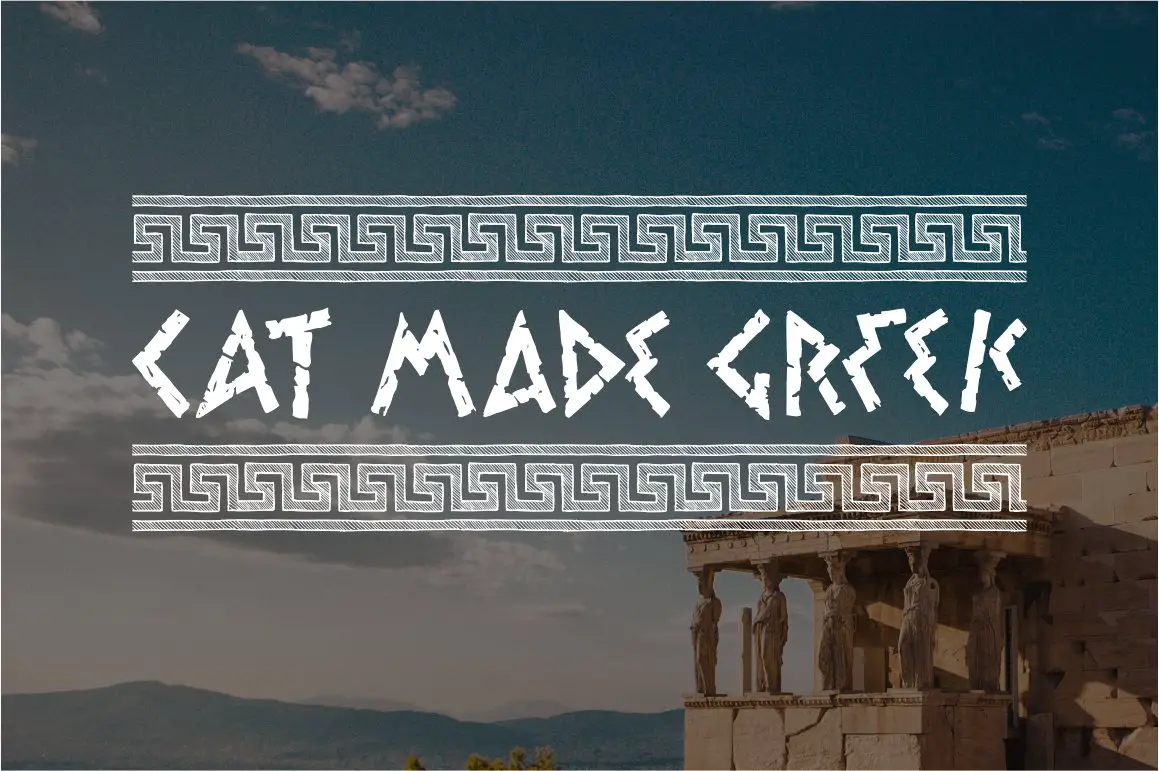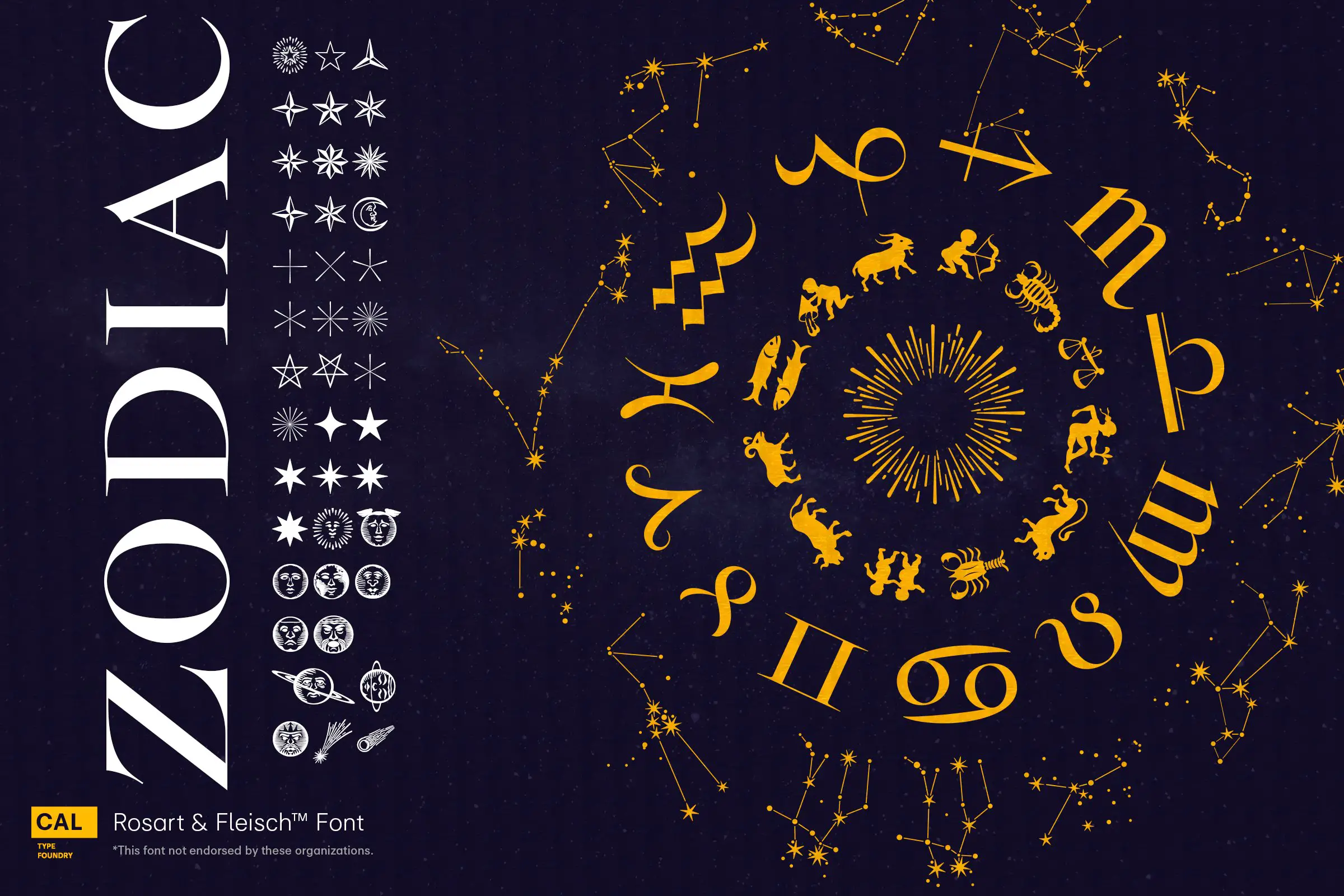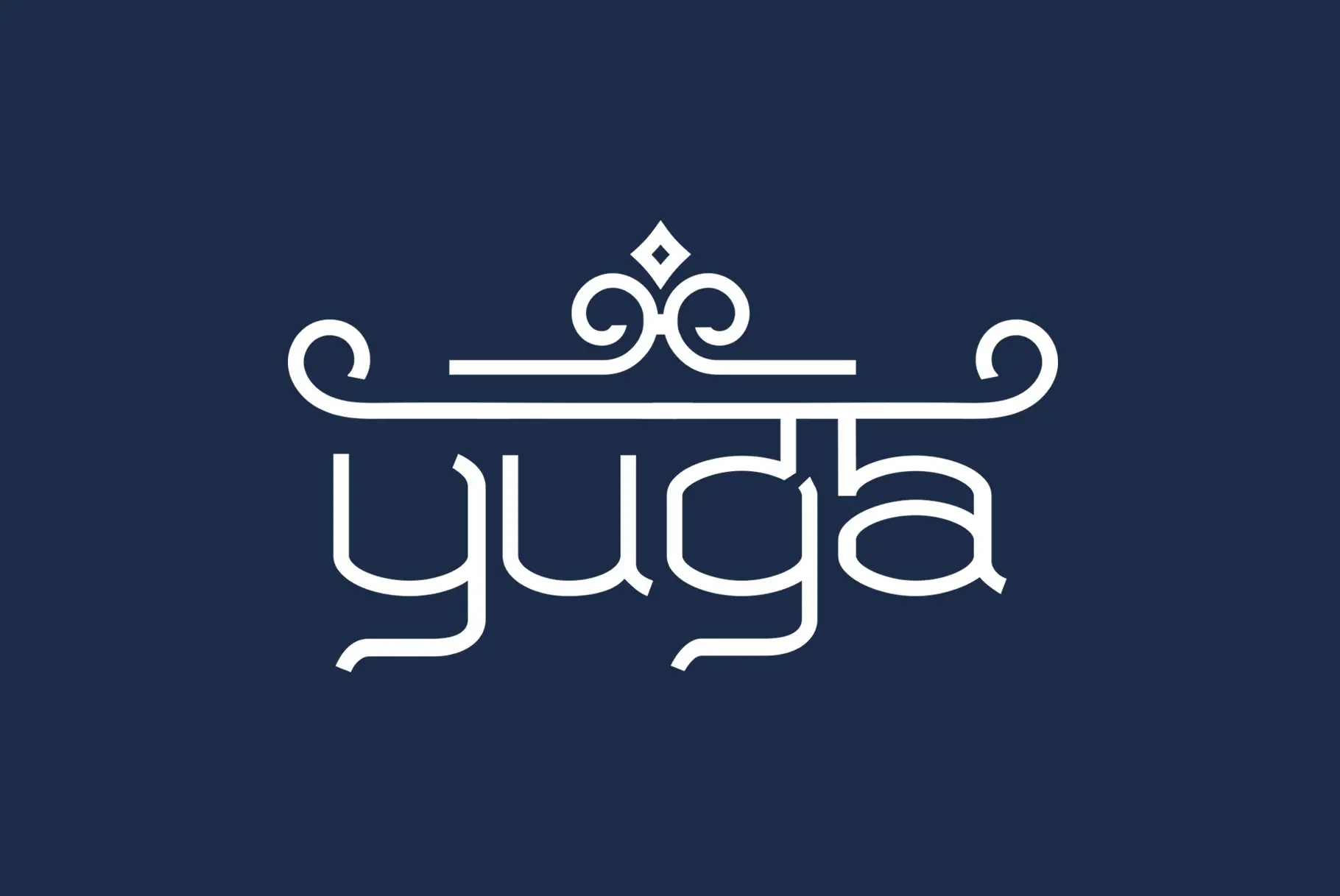
Die 16 besten Bangla-Schriftarten 2023
Veröffentlicht: 2023-05-16Sind Sie ein Grafikdesigner und suchen nach der perfekten Bangla-Schriftart, um das Design Ihres Projekts zu verbessern? Suchen Sie nicht weiter! Unser Artikel über die 16 besten Bangla-Schriftarten bietet Ihnen alles.
In diesem Artikel haben wir eine Liste der 16 besten Bangla-Schriftarten zusammengestellt, die Ihre Designs auf die nächste Stufe heben. Bei über 300 Millionen Bangla-Sprechern weltweit ist es wichtig, die richtige Schriftart zu haben, um Ihre Botschaft effektiv zu kommunizieren. Unsere Auswahl umfasst Schriftarten, die sowohl schön als auch gut lesbar sind und dafür sorgen, dass Ihre Designs hervorstechen.
In diesem Beitrag stellen wir Ihnen jede unserer handverlesenen Bangla-Schriftarten vor und geben Einzelheiten zu ihren einzigartigen Funktionen und Vorteilen. Ganz gleich, ob Sie für eine Website, einen Druck oder soziale Medien entwerfen, diese Schriftarten tragen dazu bei, dass Ihre Arbeit professionell und elegant aussieht.
Elodie
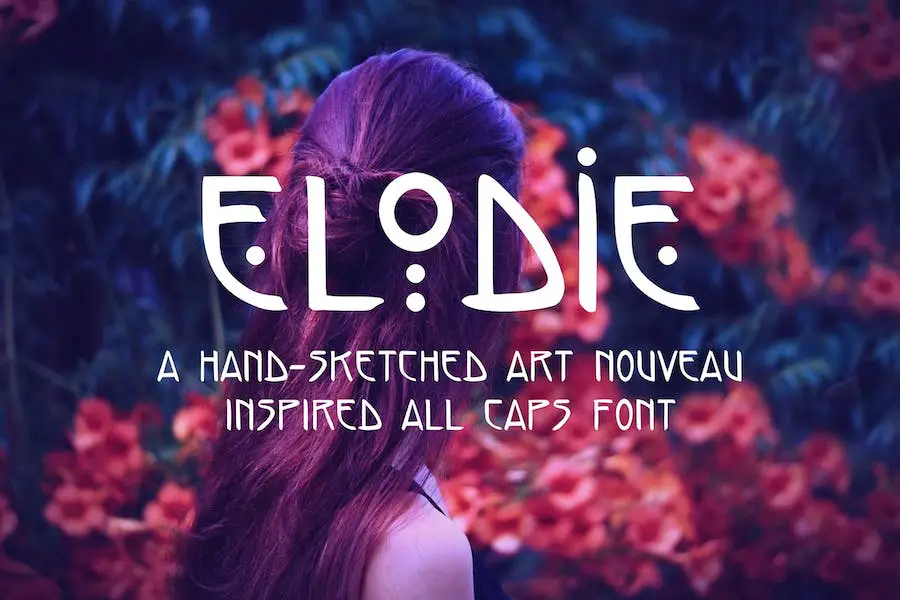
Elodie ist eine vielseitige Schriftart, die ein einzigartiges und skurriles Design für kreative Projekte bietet. Diese Großbuchstabenschrift wurde mit einem Pinselstift entworfen und verleiht ihr ein handgezeichnetes Gefühl, das jedem Projekt, an dem Sie arbeiten, mit Sicherheit eine persönliche Note verleiht.
Eines der herausragenden Merkmale von Elodie ist seine Fähigkeit, für eine Reihe von Zwecken verwendet zu werden, darunter Titel, kurze Zitate und sogar Produktnamen, und Sie können Bangla-Schriftarten in Adobe verwenden.
Agelix
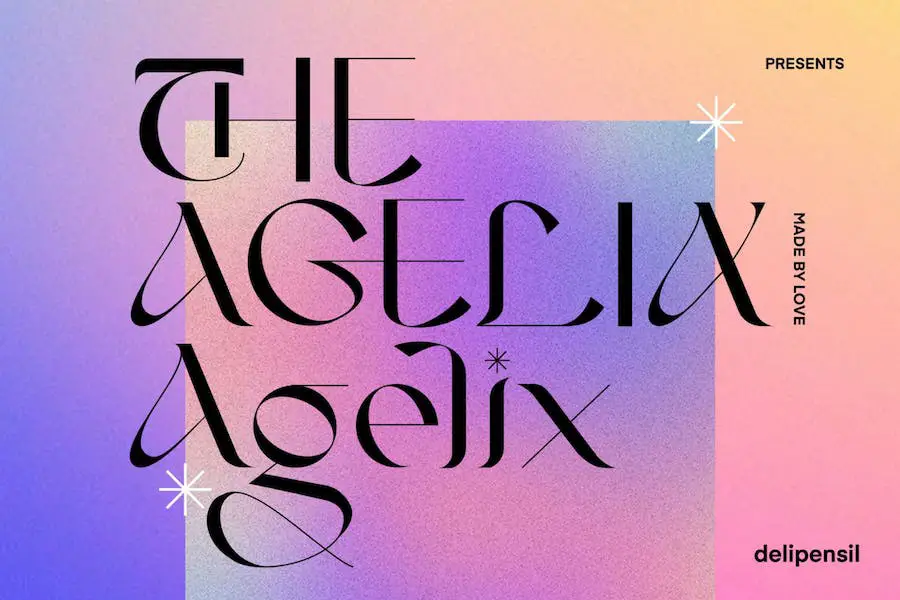
Agelix ist eine Serifenschrift, die eine perfekte Kombination aus klassischem und achtsamem Design bietet und sich für alle Schönheitsinhalte eignet. Diese Schriftart kann für verschiedene Zwecke verwendet werden, darunter Logos, Überschriften, Buchumschläge, Zeitschriften und vieles mehr.
Wenn Sie nach Bangla-Schriftarten für Canva suchen, ist Agelix eine gute Wahl. Sein klares und klassisches Design macht es perfekt für alle Beauty-Inhalte und seine Vielseitigkeit bedeutet, dass es auch für jedes andere Projekt gut funktioniert. Probieren Sie Agelix also einfach aus – Sie werden nicht enttäuscht sein!
Seelengeist
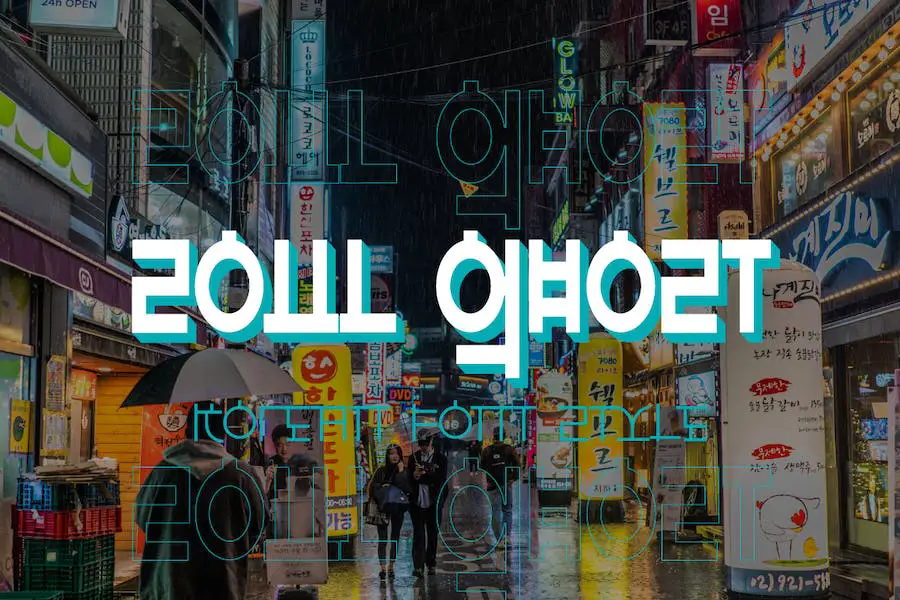
Soulghost ist eine koreanische Schriftart, die sich perfekt für diejenigen eignet, die eine Schriftart für verschiedene Designzwecke benötigen. Diese Display-Schriftart ist einfach und minimalistisch und bietet eine hervorragende Option für Logos, Zeitschriften, Social-Media-Beiträge, Broschüren und mehr.
Wenn Sie auf der Suche nach Bangla-Schriftarten für Figma sind, sollten Sie unbedingt Soulghost in Betracht ziehen. Der koreanische Stil und das minimalistische Design sorgen dafür, dass Ihre Projekte elegant und professionell aussehen.
Bocan
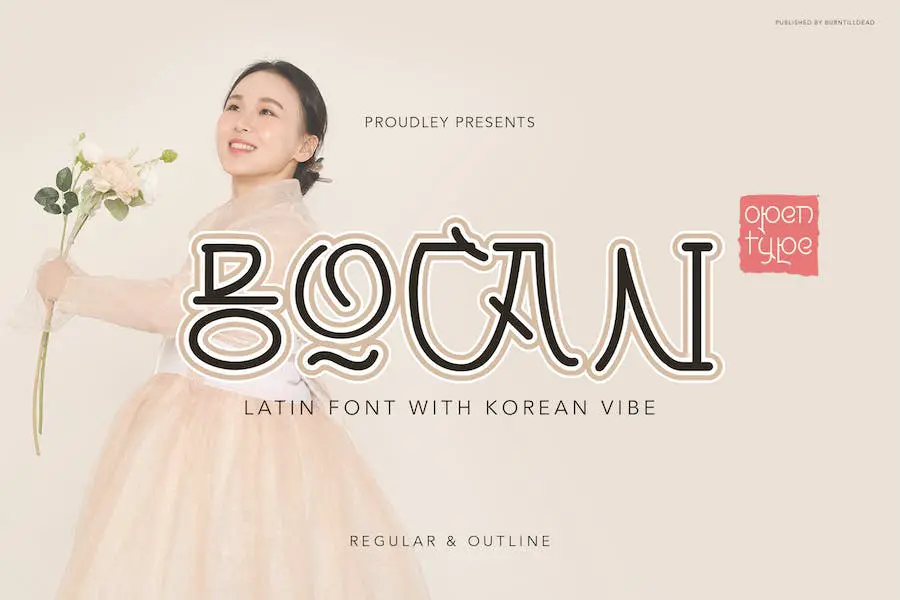
Bocan Font ist eine stilvolle Schriftart, die von koreanischen Filmcovern inspiriert ist und dadurch einzigartig und ikonisch ist. Mit zwei Stilen zur Auswahl (normal und Outline) und OpenType-Funktionen bietet Bocan Font endlose Möglichkeiten für Designer, die ihren Designs einen Hauch koreanisches Flair verleihen möchten.
Wenn Sie nach Bangla-Schriftarten für Illustrator suchen, die Ihre Designs auf die nächste Stufe heben, dann sind Sie bei Bocan Font genau richtig.
Mit seinem einzigartigen Stil und den endlosen Möglichkeiten ist es die perfekte Wahl für jedes Projekt, bei dem eine koreanische Atmosphäre gewünscht wird. Warum also warten? Beginnen Sie noch heute mit der Verwendung von Bocan Font und erleben Sie den Unterschied, den es macht!
Majime
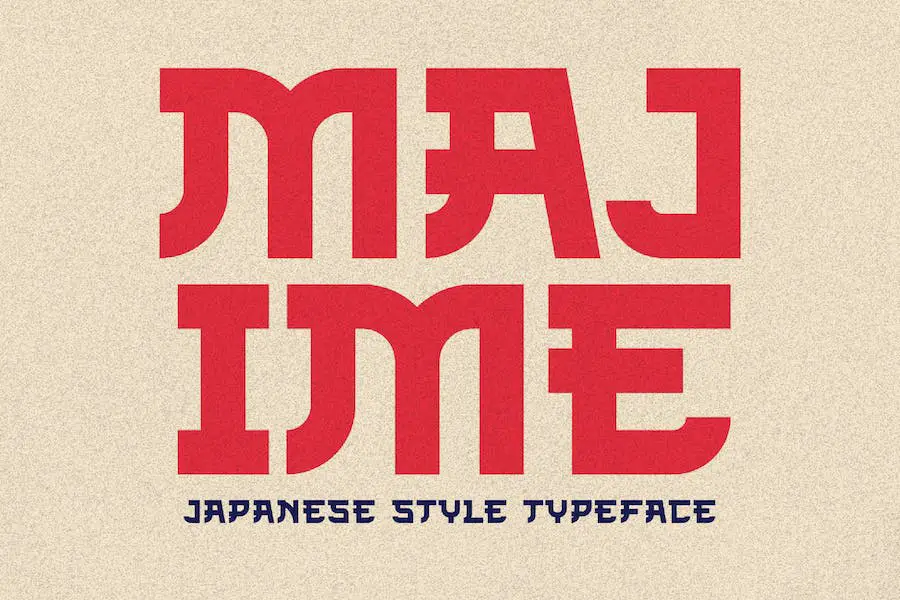
Majime ist eine atemberaubende, japanisch inspirierte Schriftart, die Ihr Designspiel auf die nächste Stufe hebt. Diese Schriftart ist sowohl in Klein- als auch in Großbuchstaben erhältlich und eignet sich daher perfekt für eine Vielzahl von Projekten.
Egal, ob Sie an einem E-Sport-Logo arbeiten, ein Poster oder einen Filmtitel erstellen, Branding-Materialien entwerfen oder sogar YouTube-Cover und Miniaturansichten erstellen, bei Majime sind Sie an der richtigen Adresse.
Eine weitere tolle Sache an Majime- und Bangla-Schriftarten ist, dass sie für die Verwendung auf Mac-Computern verfügbar sind. Dies macht es ideal für Designer, die ausschließlich auf Apple-Geräten arbeiten und eine hochwertige Schriftart benötigen, die nahtlos mit ihrem Setup zusammenarbeitet. Egal, ob Sie ein professioneller Designer sind oder gerade erst anfangen, Majime ist auf jeden Fall einen Blick wert.
Bazelle
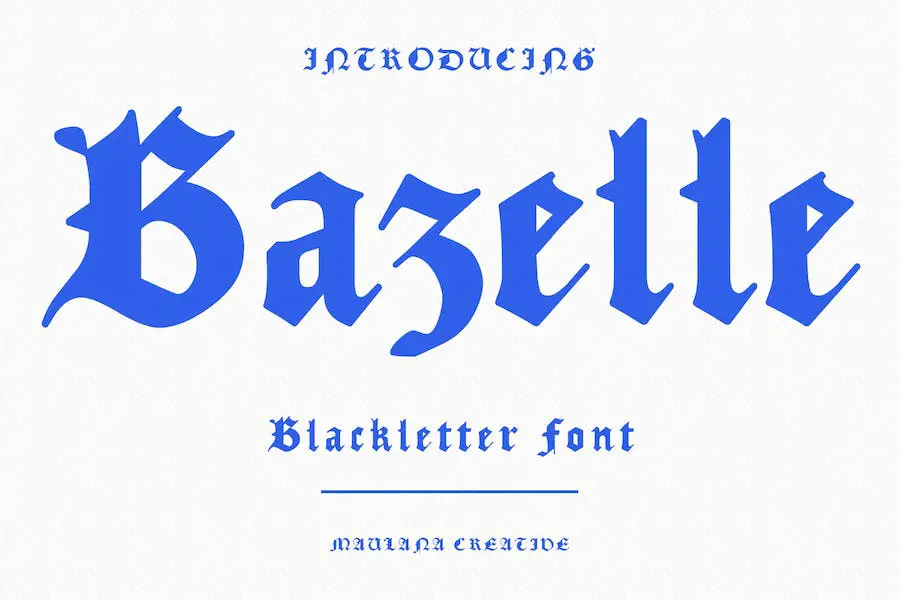
Bazelle ist eine moderne und experimentelle Blackletter-Schriftart, die über Striche mit mittlerem, geringem Kontrast, lustigen Charakter und ein wenig Ligatur und Alternativen verfügt, um Ihnen zusätzliche kreative Arbeit zu ermöglichen.